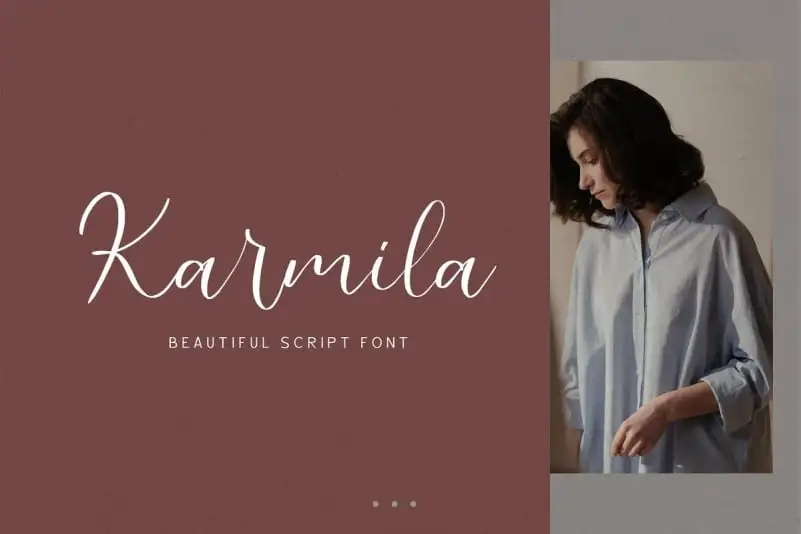
Karmila Calligraphy Font – Download Grátis
A Karmila Calligraphy Font é uma obra-prima para aqueles que buscam um toque elegante e moderno ao incorporar texto no seu design. Inspirada na tipografia script, a Karmila traz textos que se destacam pela delicadeza e sofisticação, tornando-os perfeitos para várias aplicações, desde cartões de convite até logomarcas web. A fonte foi criada pelo designer Alit Design, oferecendo um design único e naturalmente fluido por meio das ligaturas surpresa que a acompanham. Suas características únicas tornam a Karmila Calligraphy Font uma escolha ideal para variadas necessidades de design, incluindo o uso em cartazes impressos, cartões de convite, redes sociais, embalagens de produtos e sites web. Essa fonte é um verdadeiro tesouro para designers que desejam incorporar um toque autêntico e sofisticado em seus projetos.